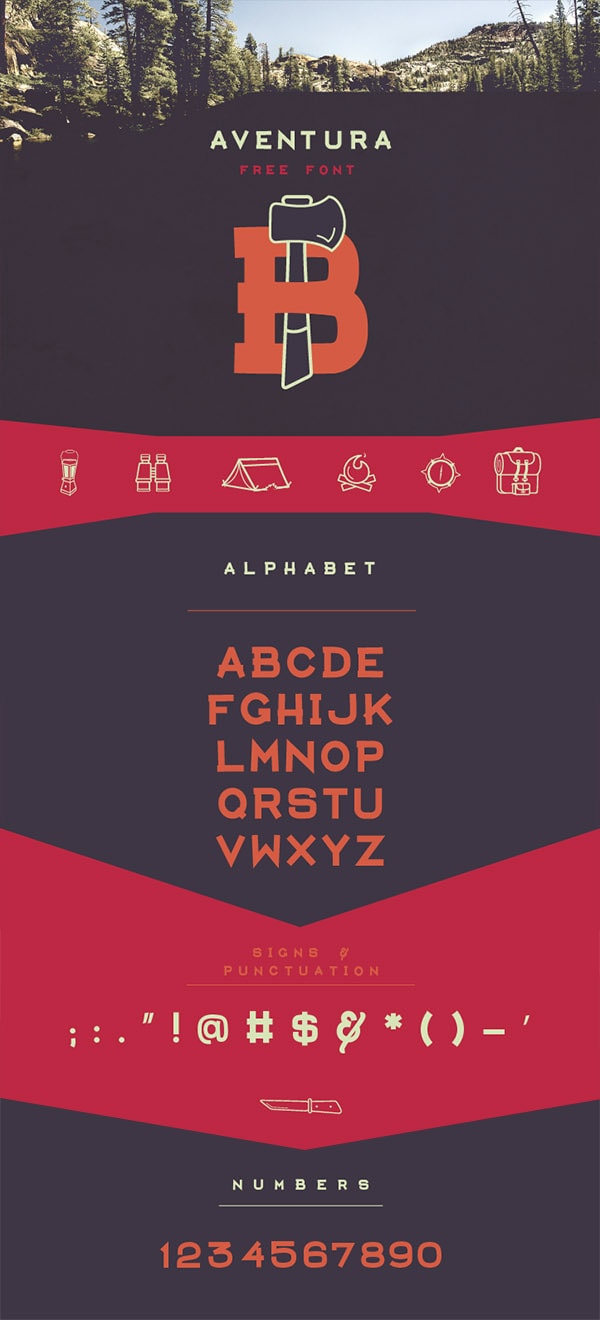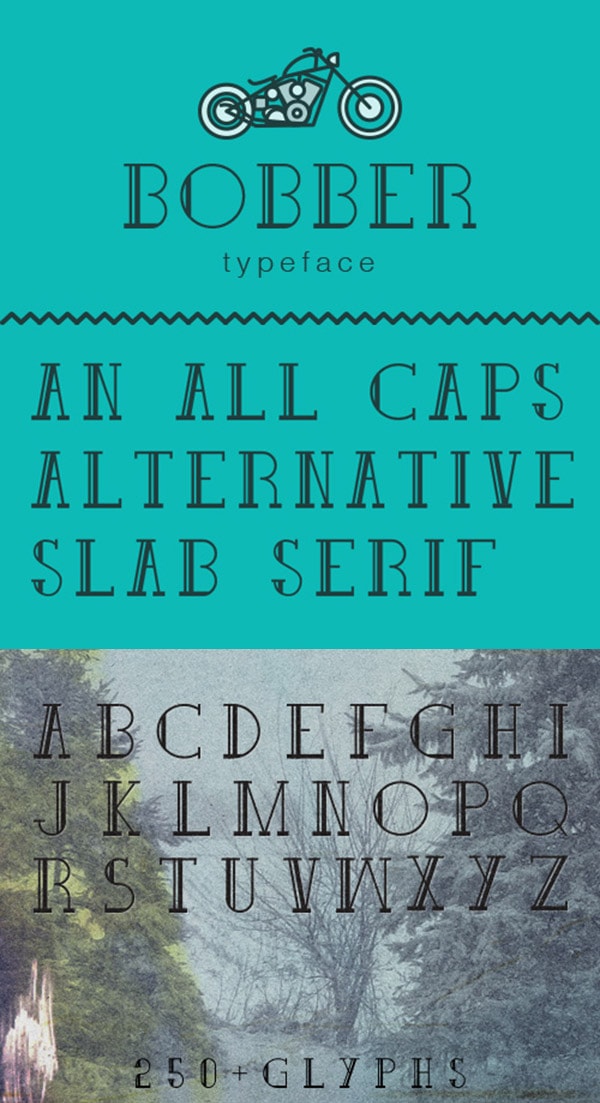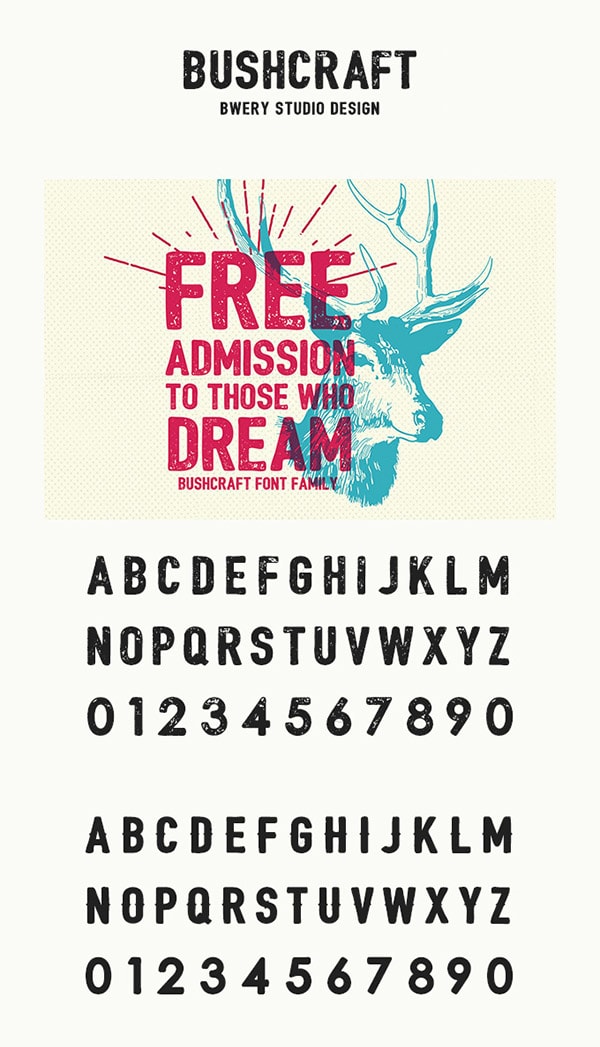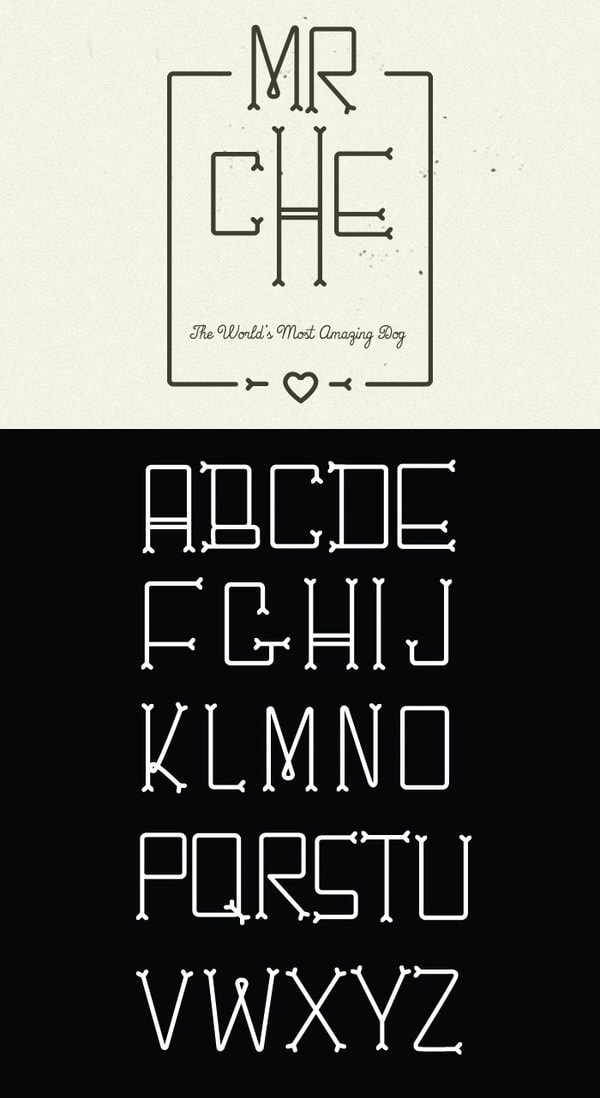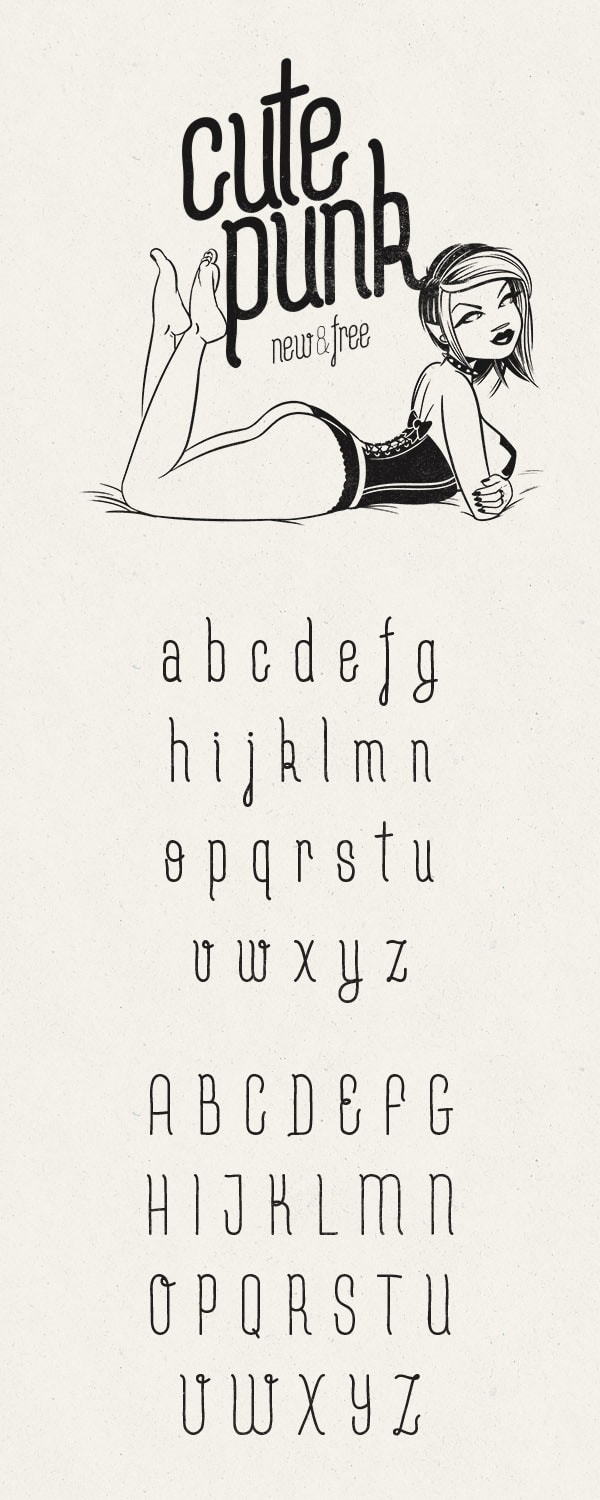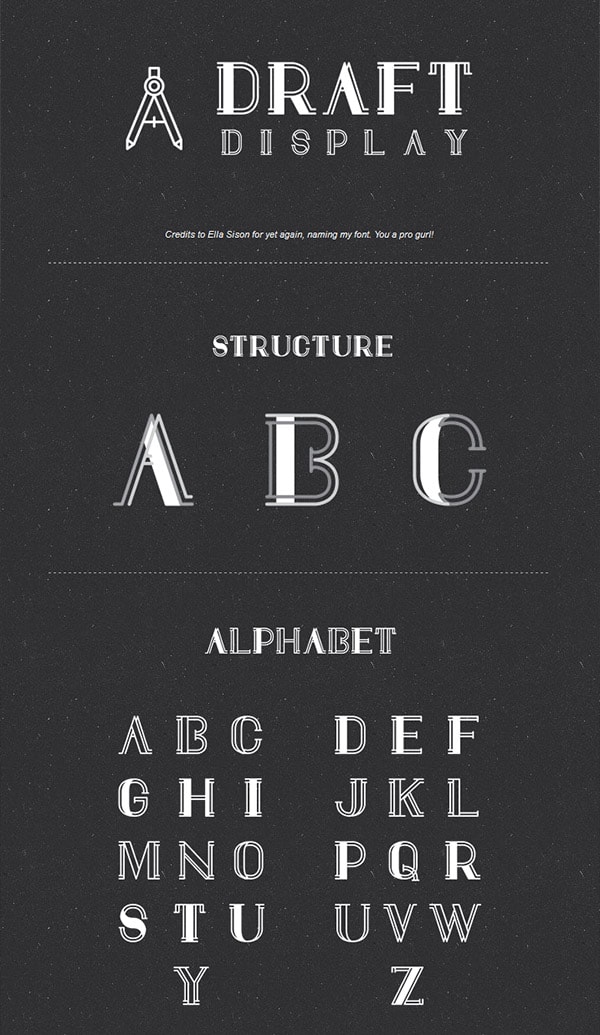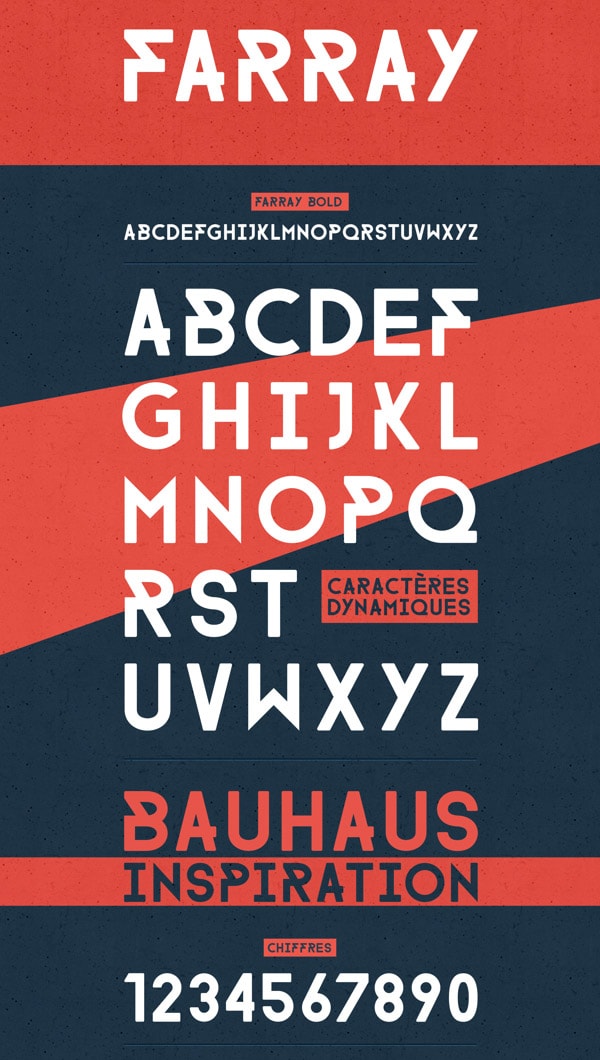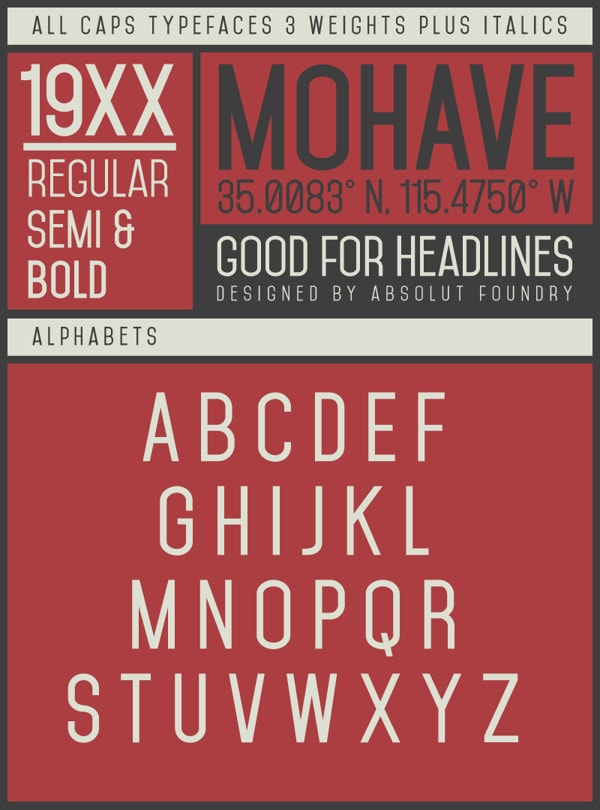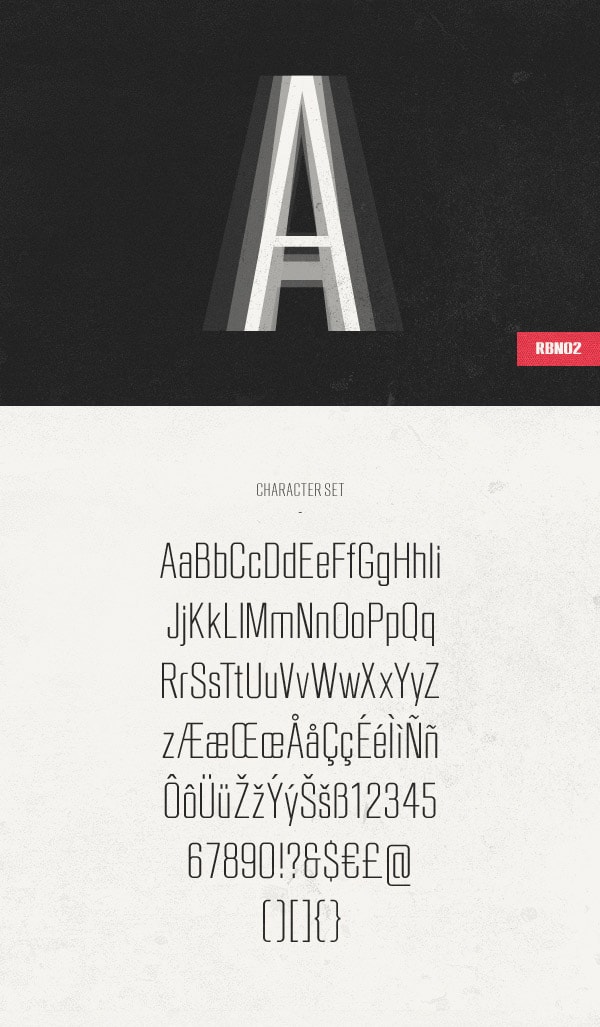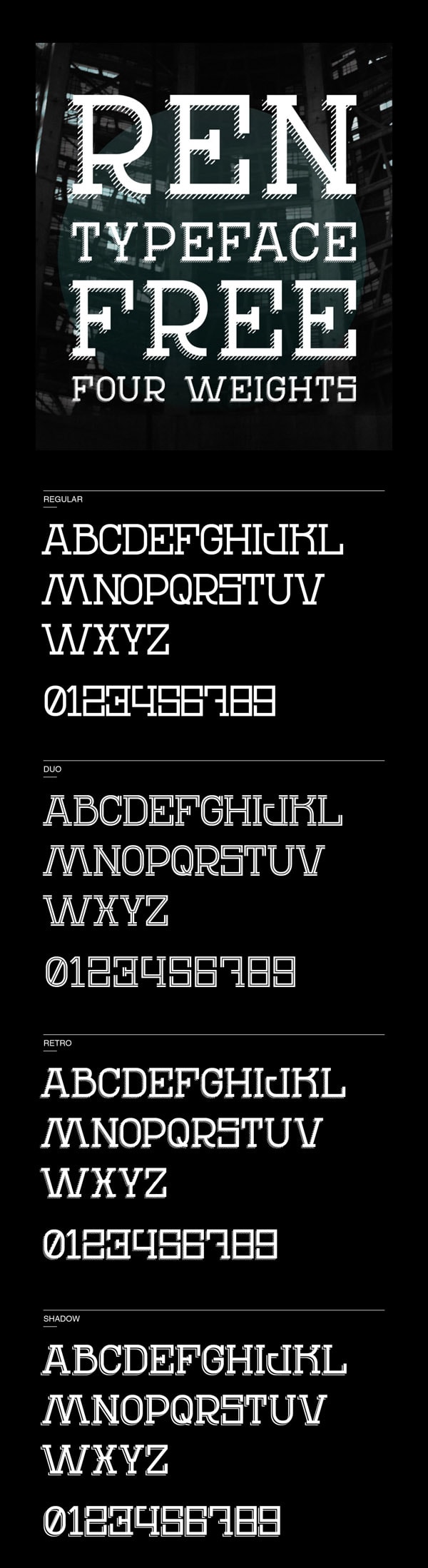
Découvrez et téléchargez 13 typographies à hipsters
Voilà longtemps que je n’avais pas proposé de typographies à télécharger sur le blog. Car la facilité a du bon, voici une petite sélection de 13 typographies sympas qui raviront les barbus fumeurs de pipes et amateurs de restaurants bobo-écolo-bio.
Je charrie, puisque je suis moi-même un bouffeur de verdure bobo-écolo-bio fumeur de pipe en fait. Certains diraient même que je suis un hipster qui s’ignore, mais je me refuse à admettre une telle ignominie. Blague mis à part, le terme cliché « typographie à hipsters » désigne surtout pour moi des typographies classes, passe-partout et sachant garder une touche de fantaisie. On ne va pas se mentir, sur des boulots à petits budgets on les trouve quand même bien pratiques ces polices d’écritures. En voici 13 piochées ici et là que je trouve personnellement aussi variées qu’utiles. Pour télécharger la typographie de votre choix, cliquez sur l’image afin de vous rendre sur la page de celle-ci.